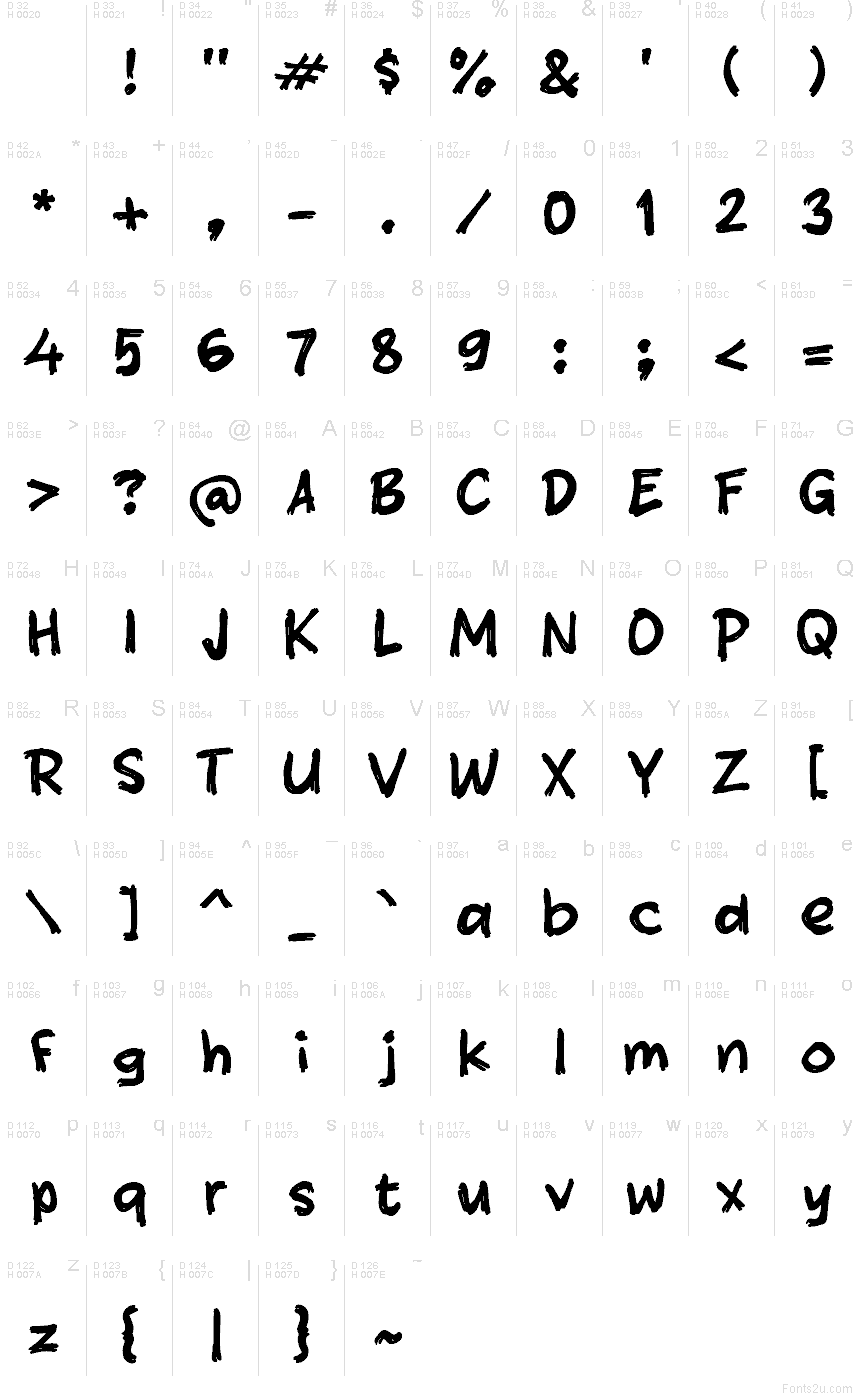
Oblade від Wep - це безкоштовний brush-шрифт із товстими, округлими штрихами та вільним, «ручним» ритмом. Літери виглядають накресленими швидко й експресивно, а не вивіреними до ідеалу: м’яке тремтіння, тупі закінчення та легка нерівність роблять текстуру живою та активною у всьому дизайні.
Ця невимушена енергія маркера чудово підходить для заголовків плакатів, обкладинок альбомів, брендингу кав’ярень, пакування та графіки для соцмереж, де надто сувора базова лінія виглядала б недоречно формально. Шрифт найкраще працює в коротких заголовках і логотипах, оскільки широкі вигини та груба динаміка надають кожному рядку самобутнього, «крафтового» вигляду, не перетворюючись при цьому на нав’язливий спецефект.
Презентація та наочний зразок шрифту Oblade
Таблиця символів шрифту Oblade